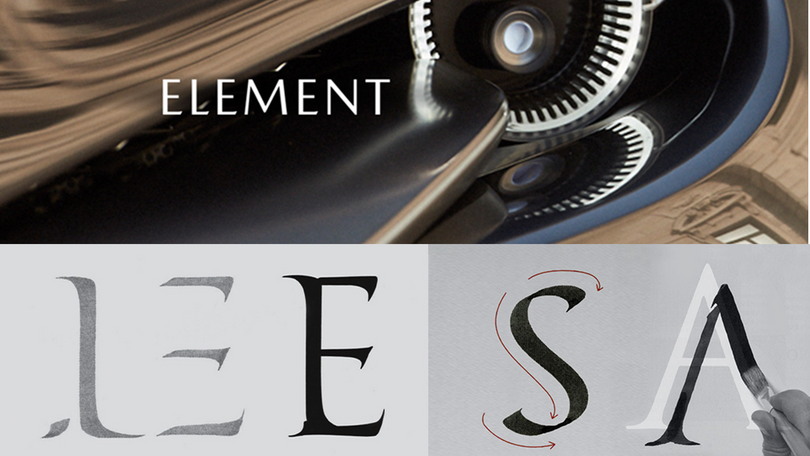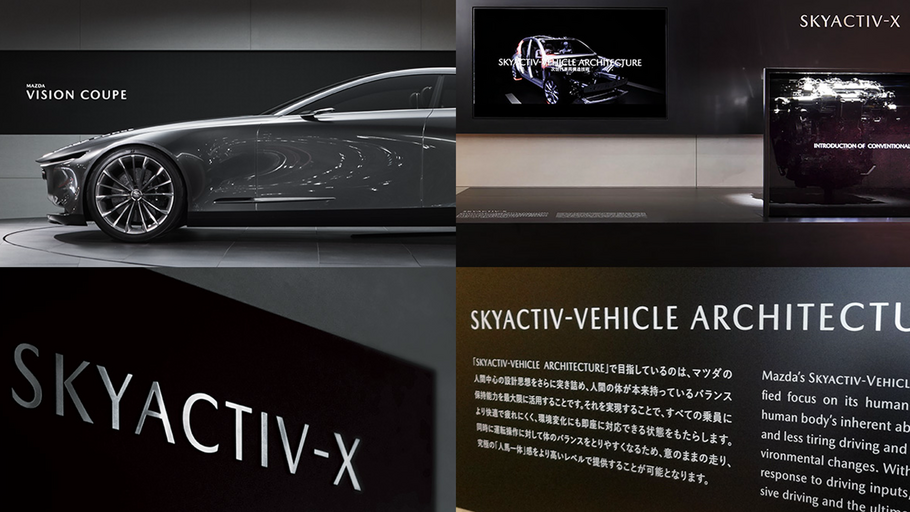
ブランドの声を表現したフォント開発:Mazda Type
Monotypeは、世界的に愛される自動車メーカーの一つであるマツダ株式会社のクルマのオーナメントに使用する英数字フォントを制作しました。マツダ株式会社は1920年に創業され、スポーティで革新的な車両デザインと技術革新で知られています。グローバルに展開し、持続可能なモビリティの推進にも注力している企業です。
2018年、商品の進化に合わせ、マツダらしさを表現するために、オリジナルフォントの開発が決定。マツダのクルマをイメージさせるモダンでありながら温かみのあるOptima のデザインや、古代ローマ碑文の文字を参考に制作が進められました。プロジェクトには、初期の段階からMonotypeのデザインチームも参加し、共同で進められました。
フォント開発にあたり最初に注目した碑文。
フォント開発にあたり、カーデザインの3つの要素、プロポーション、フォルム、エレメントといった視点をフォントデザインにも反映し、生命感や人の手による温かみを大事にするマツダのカーデザインとの親和性を追求しました。
クルマづくりでは、マツダらしさを際立たせるために、細部にまでこだわり、 文字開発でも筆圧や力の抜き加減を感じさせています。
また、「魂動-Soul of Motion」というデザインテーマのもと、国内だけでなくグローバルチーム全体で検討を幾度も重ねました。完成したオリジナルの欧文フォントMazda Typeのファミリーは、Regular、Medium、Bold とそれぞれのイタリック体を合わせた計6書体。高い視認性、視覚的な安定感、美しいプロポーションを兼ね備えており、マツダらしいブランドの声を表現するためカタログやオーナメントなどさまざまなタッチポイントで積極的に活用されています。